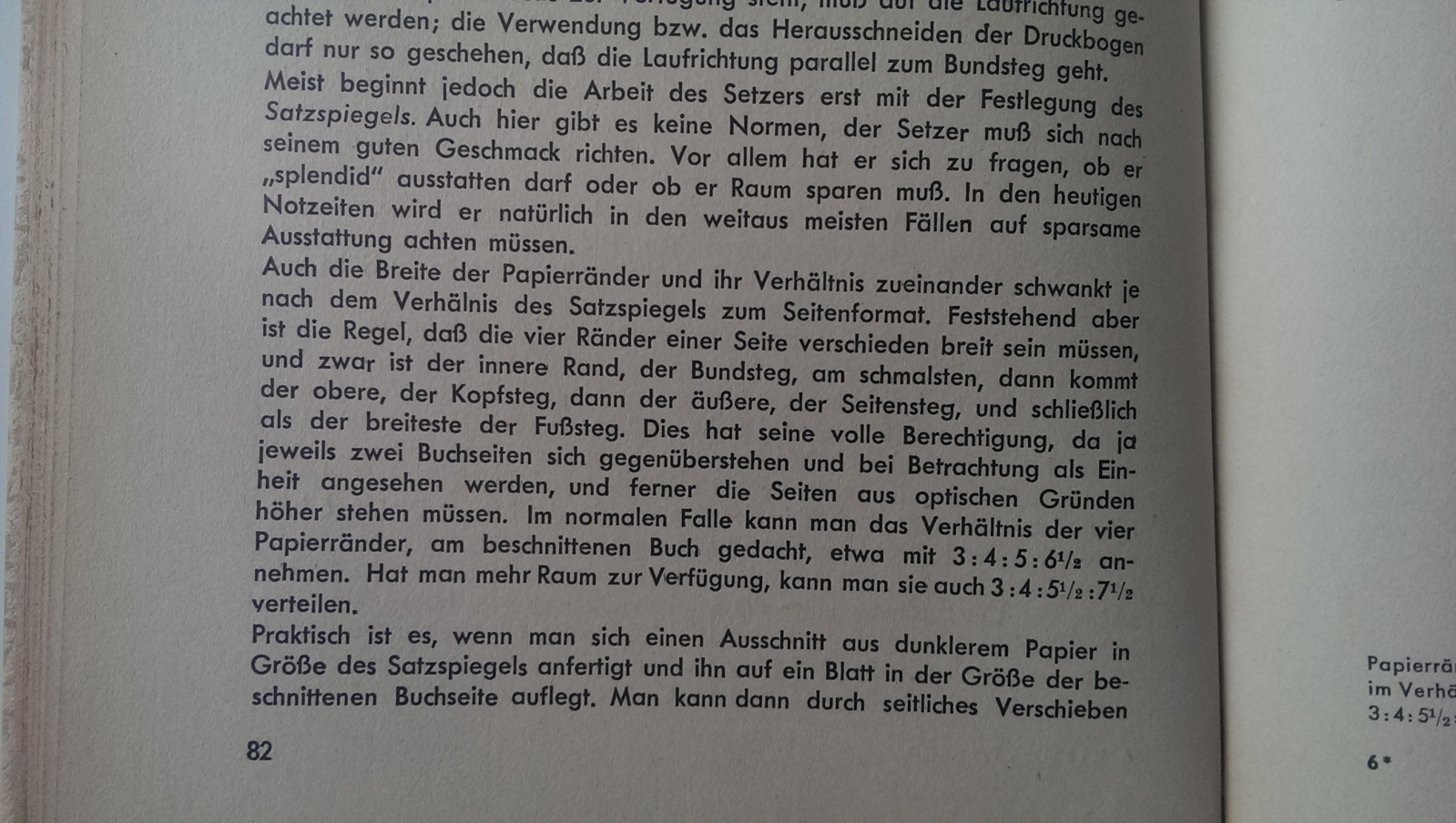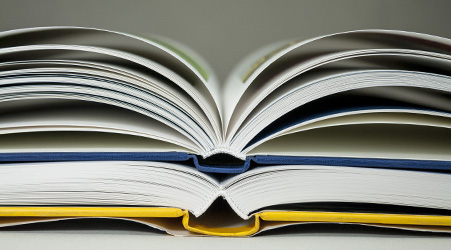
ich gebe dir recht das man keine werte wie goldener schnitt etc. als maßstab für jede buchgestaltung bzw. jedes format, jede seitenanzahl etc.nehmen sollte aber es scheint sich ja keiner dran zu halten, denn wenn ich mit die dicken romane im buchhandel anschaue oder auch die fachbücher der verlage hermann schmidt und co., so sind die spätestens ab der hälfte nicht mehr im bund lesbar. wieso ist es dann die falsche herstellung, wieso reicht es nicht den textblock auf der linken seite einfach in die obere linke und auf der rechten seite in die obere rechte ecke zu verschieben?
zu otl:
du machst hier den erfolg am layout fest, so weit würde ich nicht gegen. sicher sind das experimente, ich würde aber nicht sagen das sie nicht funktionieren. das problem ist doch eher das maße wie der goldener schnitt gelehrt werden und als standard für buch- und magazinlayout angesehen werden, dass gilt es zu hinterfragen.
Das führt schon von Anfang an in die Irre:
(wir reden doch vom goldenen schnitt)
Ich glaube nicht. Der Goldene Schnitt spielt in der konventionellen Buchtypografie nur selten eine Rolle. Ich glaube, Wagenbach macht Bücher in diesen Seitenverhältnissen, sonst fällt mir kein bekannterer Verlag ein. In wissenschaftlichen Arbeiten wäre er sicherlich falsch. Wenn Bücher nicht funktionieren, sind sie schlecht gemacht. Ich kann mit der schönen Villardschen Figur ein gutes und ein schlechtes Buch machen, dafür kann die Konstruktion nichts.
Das mit dem »einfach schieben« meinst du nicht so richtig ernst. Oder ist Typografie für dich »einfach schieben«? Dazu kann ich wenig sagen, ich finde es nie einfach.
Das modische Buch von Otl Aicher hat einen so kleinen Fußsteg, daß man die Finger immer auf der Schrift hat.
Und es funktioniert wohl auch nur deswegen, weil der Flattersatz die Zeilen auf den linken Seiten nicht durchgehend bis zum Rand füllt.
natürlich kann die villardschen figur etwas dafür, denn sie lässt keine breiten innenstege zu. schau ich mir das "meisterbuch der schrift" von tschichold an, so empfinde ich das als gerade noch möglichen wert. viel dicker hätte das buch aber nicht werden dürfen.
natürlich meinte ich das ernst. wir hier am computer schieben, es heisst ja nicht das man deshalb typografische konventionen missachtet.
Das führt schon von Anfang an in die Irre:
Ich glaube nicht. Der Goldene Schnitt spielt in der konventionellen Buchtypografie nur selten eine Rolle.
Ja, bitte klassischer Satzspiegel und goldener Schnitt auseinanderhalten. Ein klassischer Satzspiegel über Diagonalkonstruktionen hat gewisse ästhetische und praktische Argumente in Herstellung und Nutzung. Und er ist natürlich vor allem traditionell und damit ein gewohntes und damit erwartetes Bild – das ist ja nicht zu unterschätzen.
Die Wahl konkreter Verhältnisse im Sinne des goldenen Schnittes im klassischen oder irgendeinem anderen Satzspiegel ist dagegen eher Vodoo. Ich sehe keine plausiblen Gründe, warum eine errechnete Teilung von 17,5 Millimeter irgendwie automatisch praktischer oder ästhetischer sein solle als 18,5 Millimeter oder irgendein anderer Wert. Zu solchen Vorgaben greift man eher, wenn man hilflos ist und sich nicht auf sein Auge verlassen will, oder aber den Auftraggeber mit dem tollen Begriff goldener Schnitt beeindrucken will.
ok. dann habe ich wohl den goldenen mit dem klassischen zusammengeworfen.
ich meinte den klassischen seitenspiegel.
... und auch der alte klemm (der verschiebt übrigens auch) lehrte das leider so.
optik vor nutzbarkeit? form follows funktion wurde anscheind später erfunden.
quelle: karl klemm, typografie lehr- und handbuch, band 1
natürlich kann die villardschen figur etwas dafür, denn sie lässt keine breiten innenstege zu. schau ich mir das "meisterbuch der schrift" von tschichold an, so empfinde ich das als gerade noch möglichen wert. viel dicker hätte das buch aber nicht werden dürfen.
Ist das Meisterbuch mit der Villardschen Figur konstruiert? Kann ich kaum glauben. Hast du das nachgemessen? So einen Bildband würde ich nicht so einrichten. Tschichold hat ja in seinen Büchern deutlich mehr Möglicheiten angegeben. Ich finde den Bundsteg dort auch etwas zu eng.
Wenn man den Außensteg schmal macht und den inneren dann halbiert, dann wird der innere wohl zu schmal werden. Das haben die Leute früher nicht gemacht. Alte Bücher haben keine zu engen Bundstege. Meine Produktionen übrigens auch nicht. Ich hab vor fünf Jahren eine Reihe ausgestattet, die seither im Innern unverändert produziert wird. Fotos davon gibt es hier.
Das Lehrbuch von Klemm kenne ich nicht. Aber er handelt in einem kleinen Absatz ab, womit Tschichold ganze Bücher gefüllt hat. Wenn ich das nicht falsch verstehe. Also das sichtbare kleine Stück bei Klemm reicht nicht für Buchentwurfsüberlegungen.
Was Ralf anmerkt zur Konstruktion, hat Paul Renner in seinem Typografiebuch beschrieben: Man konstruiere und lege dann die gedruckte Seite in den Blindband und »schiebe« (ja!) die Kolumne dann an eine richtige Stelle. Es kommt nicht auf den konstruierten Millimeter an, die Konstruktion ist eine Hilfe, ein Ausgangsgerüst, damit es eben »willkürfrei« (Tschichold) zugeht. Dieses letzte Schieben für de Feinjustierung kann man nur gut machen, wenn man entweder einen Blindband hat oder weiß, wie sich Format, Bindung, Papier verhalten. Der Typograf muß mit dem Hersteller reden, der Hersteller sich auf die Bindung festlegen und auf alles andere, bevor der Satzspiegel gemacht wird. Die meisten Buchentwürfe werden heute binnen Minuten in Agenturen zusammengenagelt, die Publikumsverlage haben keine angestellten Entwerfer mehr, und sie haben damit auch das Wissen verloren, wie gute Bücher aussehen. Die meisten Verleger verstehen heutzutage nichts von der Form des Buches. Deshalb sind Bundstege zu eng, also wegen Verletzung der Konvention und nicht wegen der Konvention.
Ich habe ja auch nicht gesagt, dass der Buchbinder das Papier weicher macht, aber im betreffenden Fall liegt eben hinter den einzelnen Heften des Buchblocks fast eine 2mm dicke Schicht recht harter Schmelzkleber, während auf dem anderen Buch hier nur mit einer hauchdünnen Kleberschicht eine Gase aufgeleimt ist.